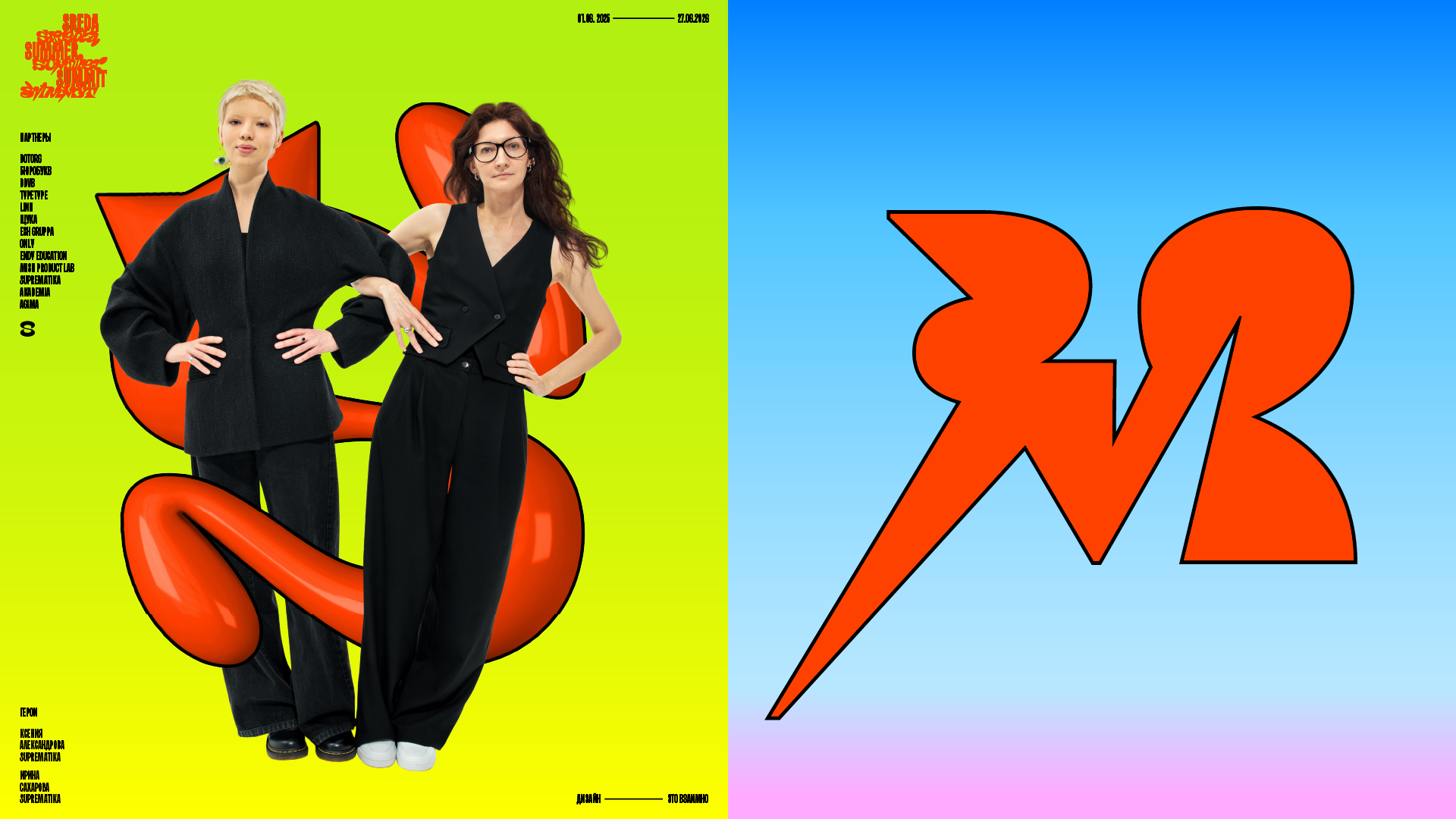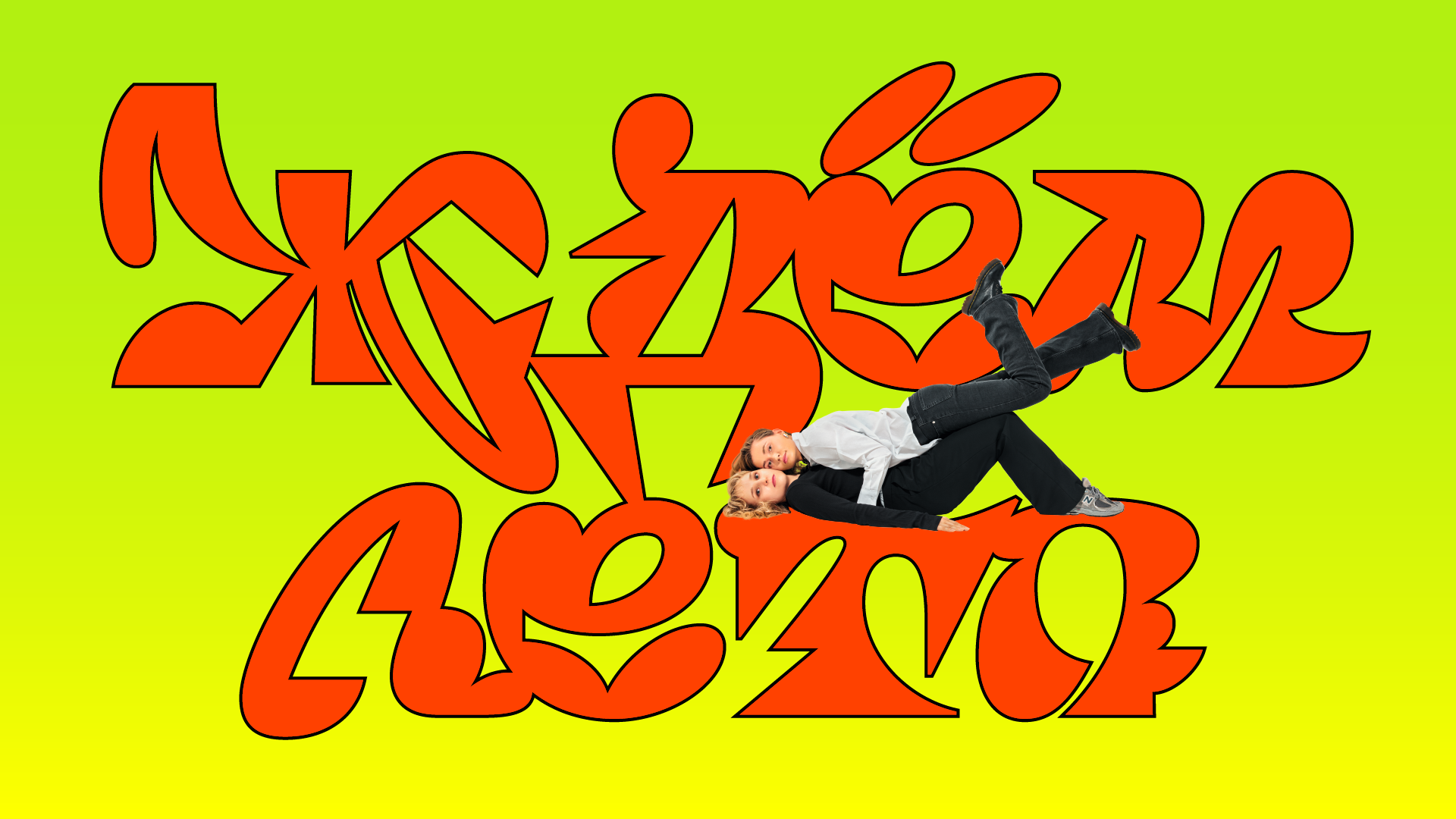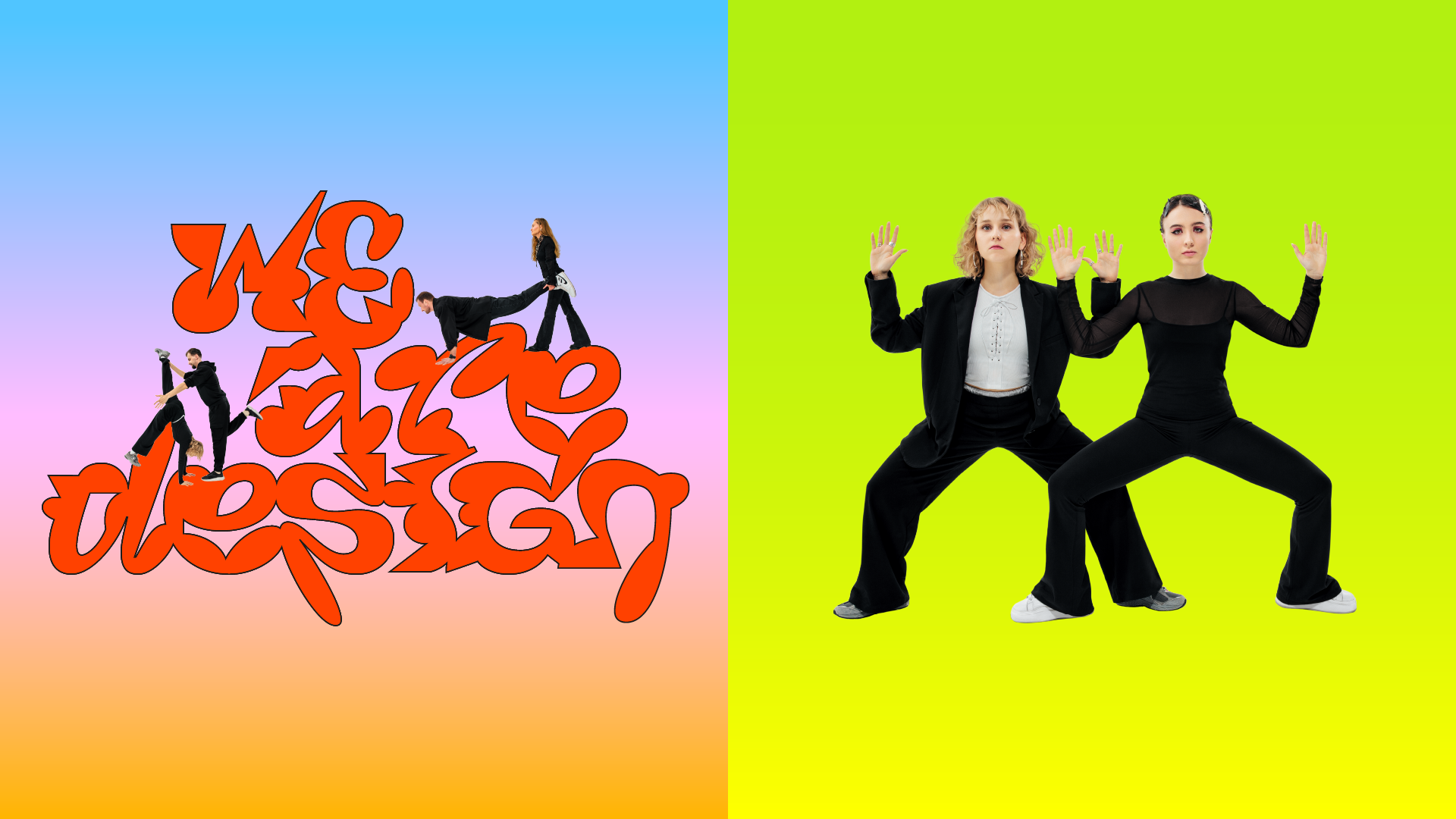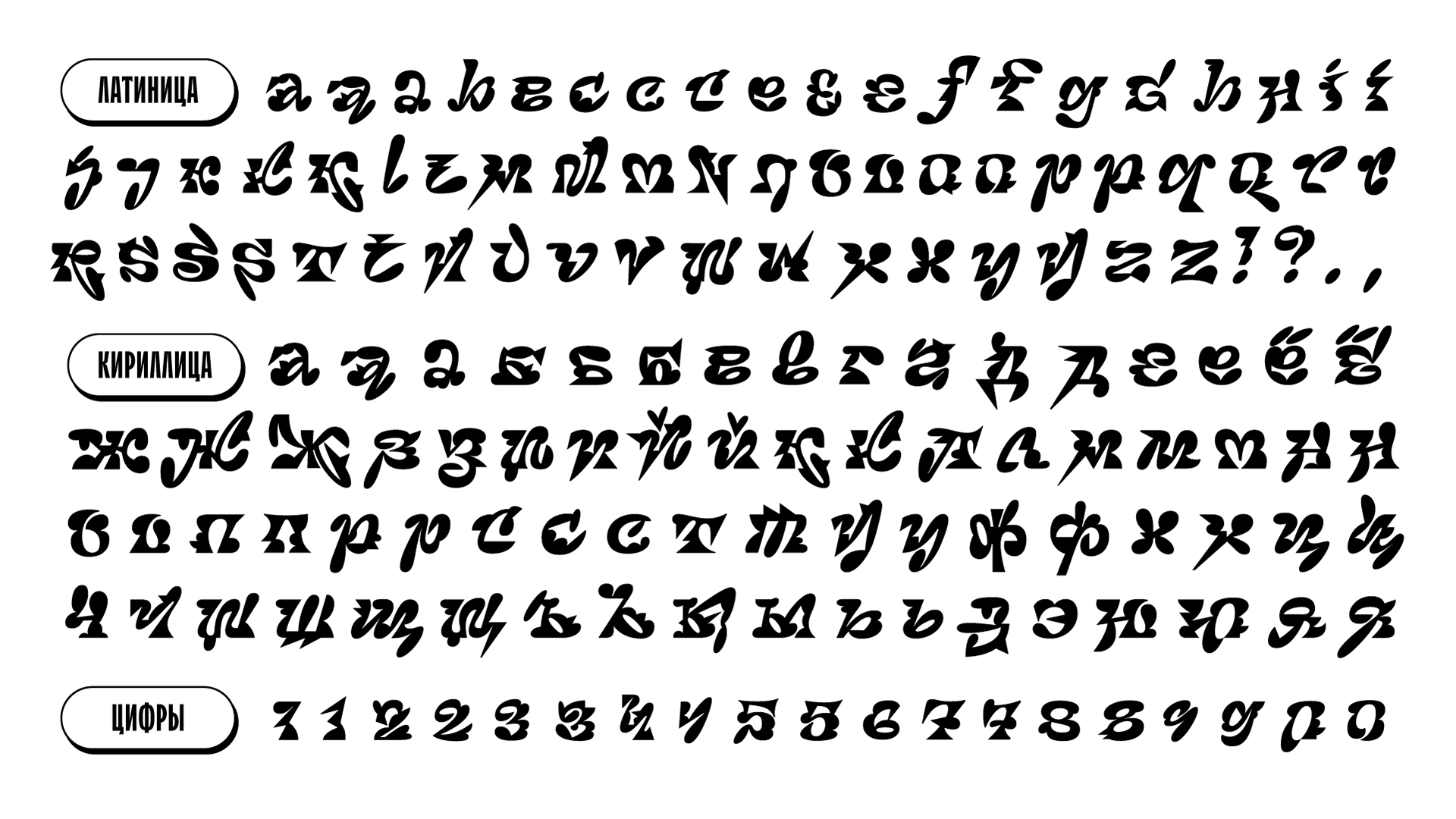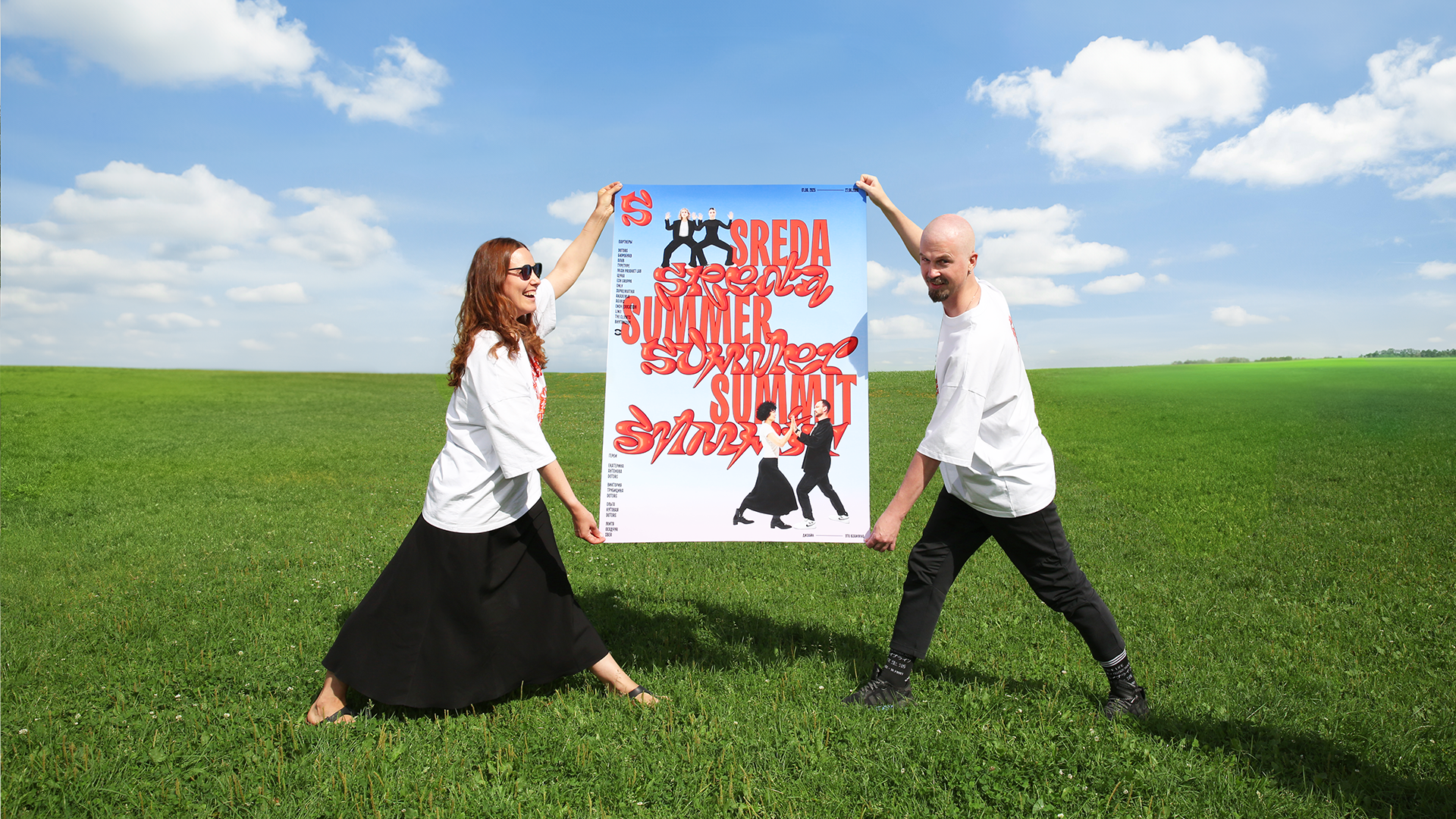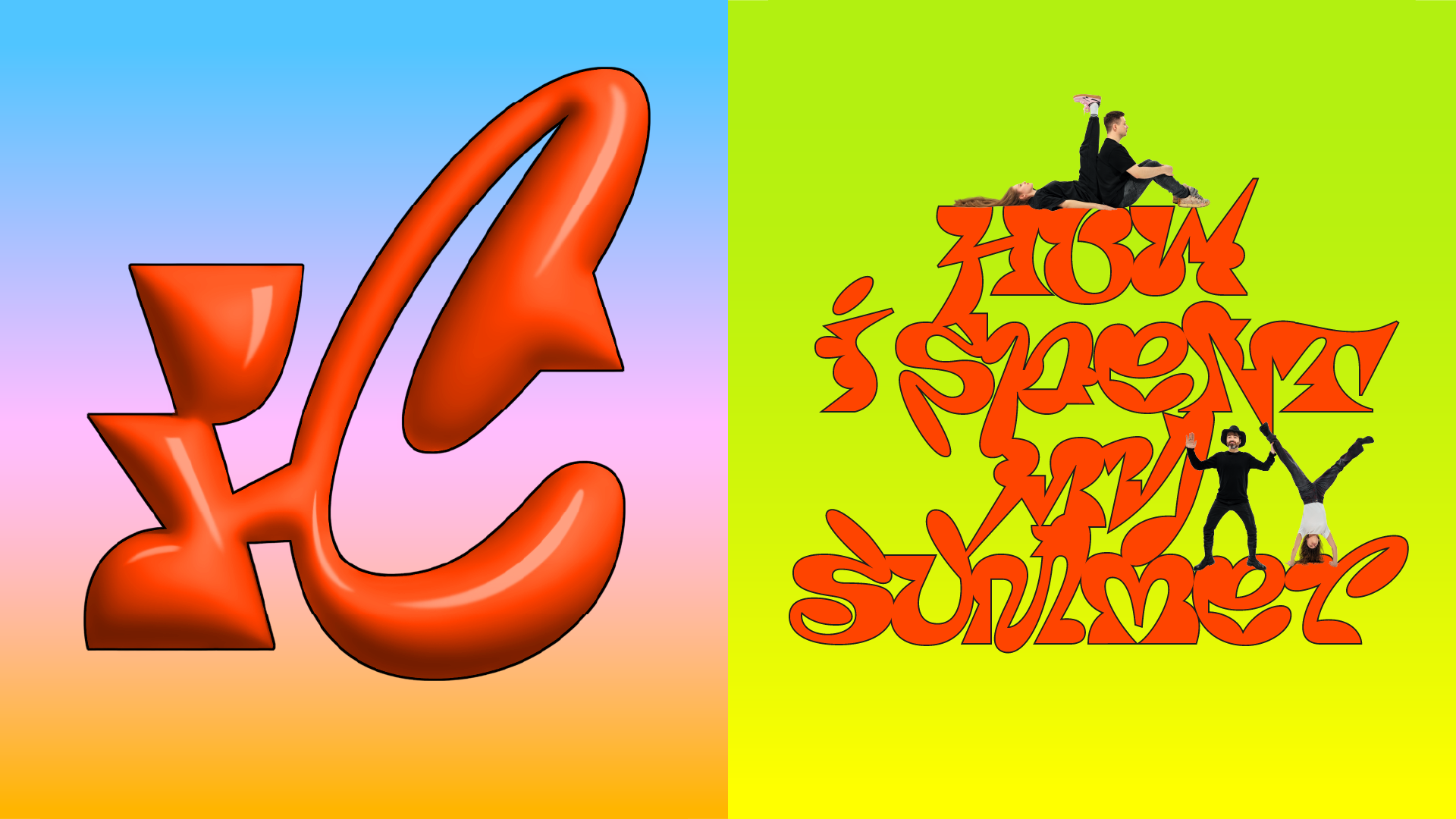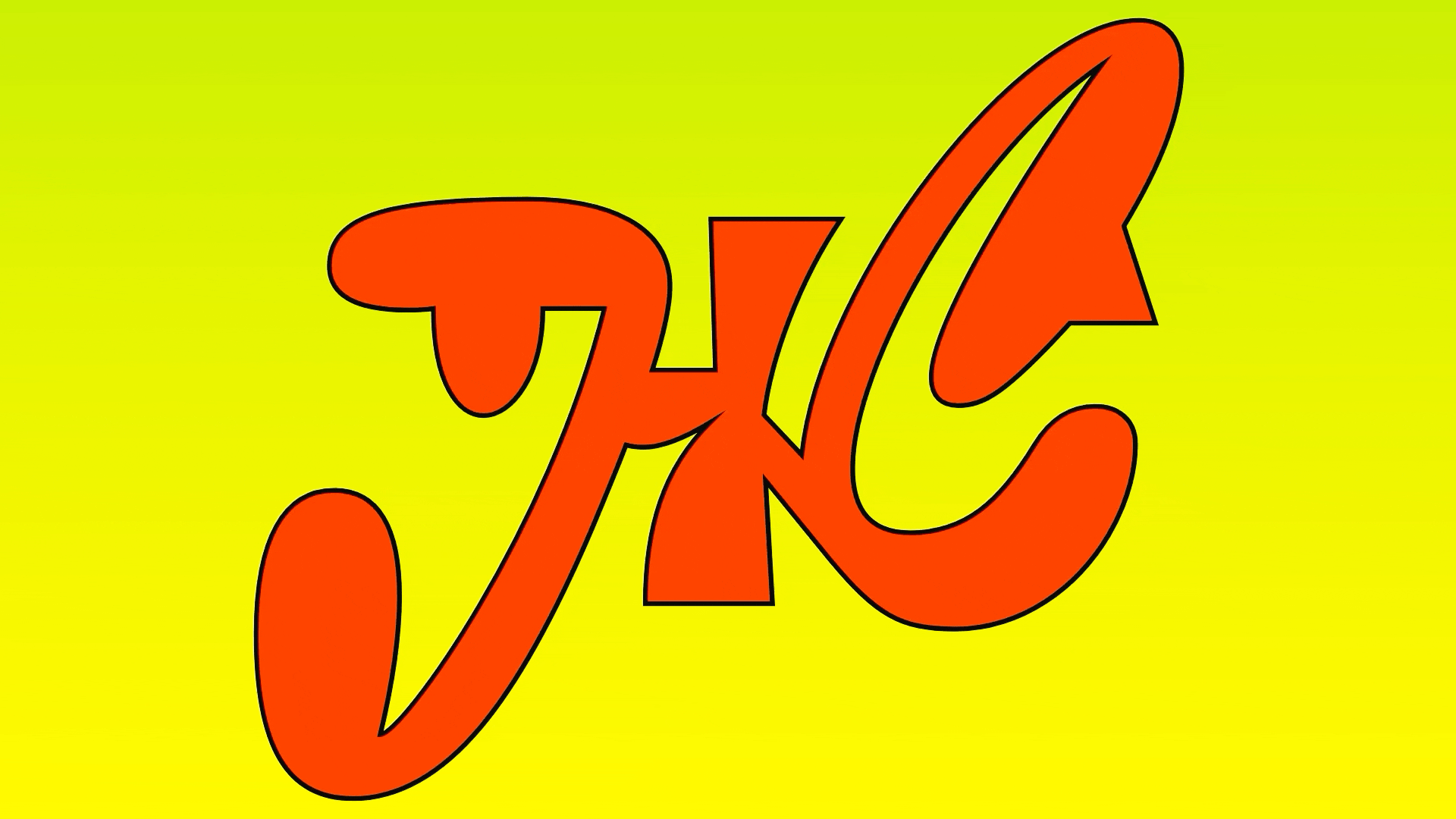
Экспериментальный шрифт
Sreda Summer Sussy
Sreda Summer Summit — это летний фестиваль дизайна, на котором происходит обмен опытом между участниками индустрии.
Метафора проекта — взаимодействие. Мы выразили её через шрифт, показывая общение самих дизайнеров с помощью типографики. Где-то мы — коллеги: поддерживающие, надёжные. А где-то — конкуренты: колючие, игривые, нарушающие границы друг друга.
Бриф от Dotorg для самих себя звучал как «упор на упоротый шрифт», а для нас как «ура, мы делаем упоротый шрифт!»
. И вот результат: с одной стороны мягкий и плавный, а с другой — дерзкий и шипастый, сложный и не сразу понятный шрифт, такой, как и все мы. А главное — он не про голую функцию, но про характер, настроение, идеи и оригинальность. Противоречивый и задорный, красивый и немного странный, но точно незабываемый.
Dotorg & Sreda Summer Summit
Бюробукв